日文字体大全,使用率 TOP 12 的日文字体推荐
或许你曾被动漫、游戏中的精美日文字幕所吸引,又或许你在设计项目时,正为如何挑选一款合适的日文字体而苦恼。别担心,本篇文章给大家介绍日文字体的特点、使用场景,重点给大家分享12款使用率比较高的日文字体。
一、日文字体的定义
日文字体,与我们汉字一脉相承,同时又有独特的构成:汉字、平假名、片假名、罗马字。这四种不同来源、不同形态的文字元素,共同构成了日文字体独特的视觉语言。一款优秀的日文字体,不仅要在每一种文字上都做到美观、统一,更要处理好它们之间的和谐共存,确保整体排版的美感和阅读的流畅性。
二、日文字体的特点:
字符集庞大且复杂
如前所述,一套完整的日文字体需要同时包含汉字、平假名、片假名、拉丁字母、数字和符号。这意味着设计师在创造一款日文字体时,需要付出比设计纯拉丁字母字体多得多的努力,以确保所有字符在视觉上保持一致的风格和比例。
注重阅读的流畅性与节奏感
优秀日文字体在字形结构、字间距、行间距的调整上都非常讲究,旨在营造一种自然、舒适的阅读节奏。例如,平假名的设计通常会比汉字更圆润、更具连笔感,以引导视线流畅地滑过。
字重与字宽的精细控制
为了适应不同场景的需求,许多日文字体都会提供一系列的字重(粗细,如细体、常规体、粗体)和字宽(宽度,如标准、窄体、宽体)选择。这使得设计师在排版时有更大的灵活性,可以根据信息层级和视觉强调来选择最合适的字形。
三、日文字体的使用场景
- 儿童或休闲品牌:圆体或活泼的POP体、手写体能营造亲切、可爱的形象。
- 标题与导航:可选用略粗的哥特体或具有辨识度的圆体,以突出信息层级。
- 游戏或动漫应用:这个场景大家应该比较常见,POP体、手写体或特定风格的创意字体能增强沉浸感和主题氛围。
- 海报与广告:POP体、粗壮的哥特体或艺术毛笔体能有效抓住眼球,传达广告信息。
- 电影、电视剧:通常选用清晰、不分散注意力的哥特体或明朝体。
- 游戏:根据游戏类型选择,像素字体、科幻字体、魔幻字体等都可能出现。
濑户字体
濑户字体是一款广受欢迎的日系手写字体,由日本设计师濑户文美创作。它以其亲切、自然且略带圆润的笔触著称,字形结构活泼可爱,充满温度感,仿佛手写笔记般真实而富有情感。
濑户字体独特的日系手写风格,笔触自然流畅,充满人情味和亲和力。字形圆润,整体风格偏向可爱和治愈,能有效营造轻松愉悦的氛围。
TanukiMagic
TanukiMagic 是一款充满奇幻色彩和独特个性的字体,其设计灵感可能来源于日本传说中的“狸猫”,融合了魔幻与可爱的元素。字体通常带有俏皮的装饰或不规则的笔画,营造出一种神秘而有趣的氛围。
字体适用于游戏Logo、奇幻小说封面、动漫标题、儿童故事书、主题乐园宣传、节日派对海报、创意市集招牌等场景。
瀞ノクーゲル黒体
瀞ノクーゲル黒体是一款具有现代感和独特设计理念的黑体字体。它在传统黑体的基础上,融入了圆润或流线型的元素,使其在保持黑体字力量感的同时,增添了一份柔和与科技感。
字体常用在科技产品发布、汽车品牌宣传、现代建筑设计、APP界面、电商平台、企业Logo、高端时尚杂志标题、广告海报。
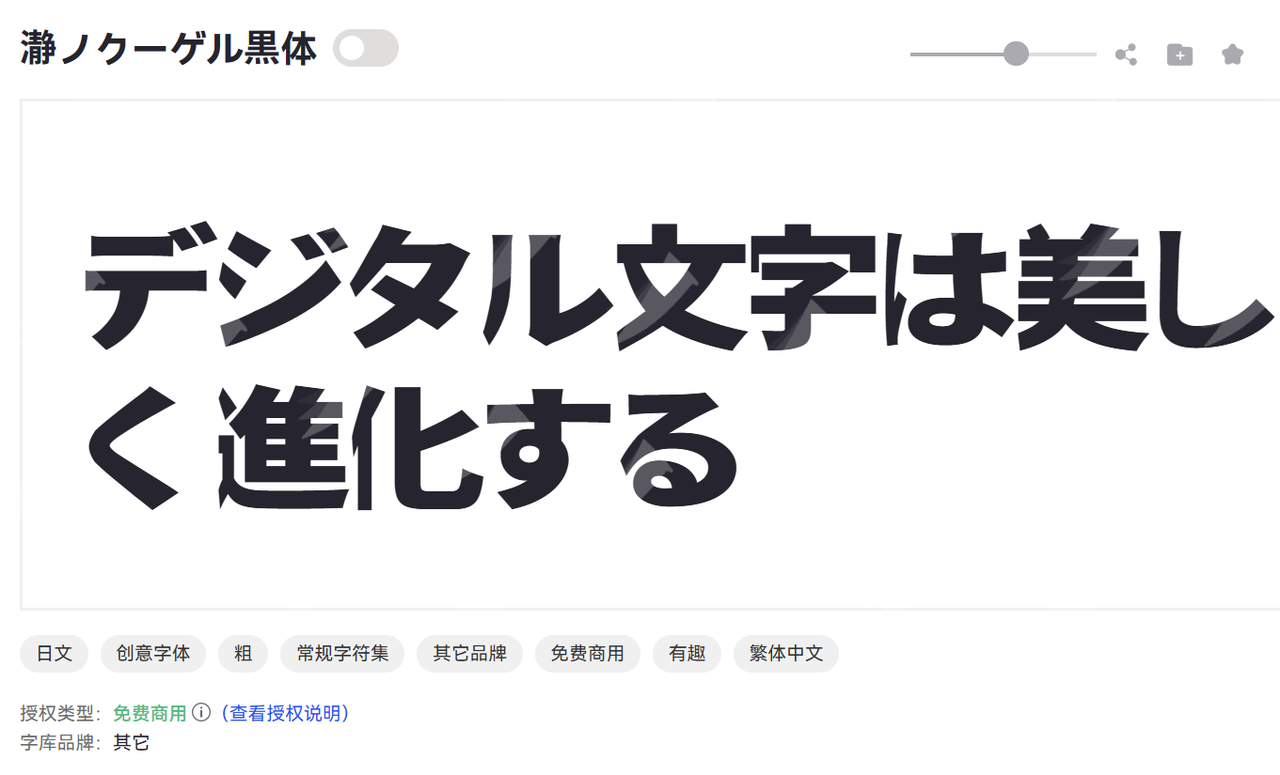
Dela Gothic One Regular
Dela Gothic One Regular是一款极具视觉冲击力的粗体无衬线字体。其笔画粗壮有力,字形结构扎实,强调了力量感和存在感,适合在需要强烈视觉表现的场景中作为标题或醒目文字使用。
字体极其粗壮的笔画使其在任何尺寸下都具备强大的视觉存在感,瞬间吸引眼球。无衬线设计保证了其现代感和简洁性,易于搭配。
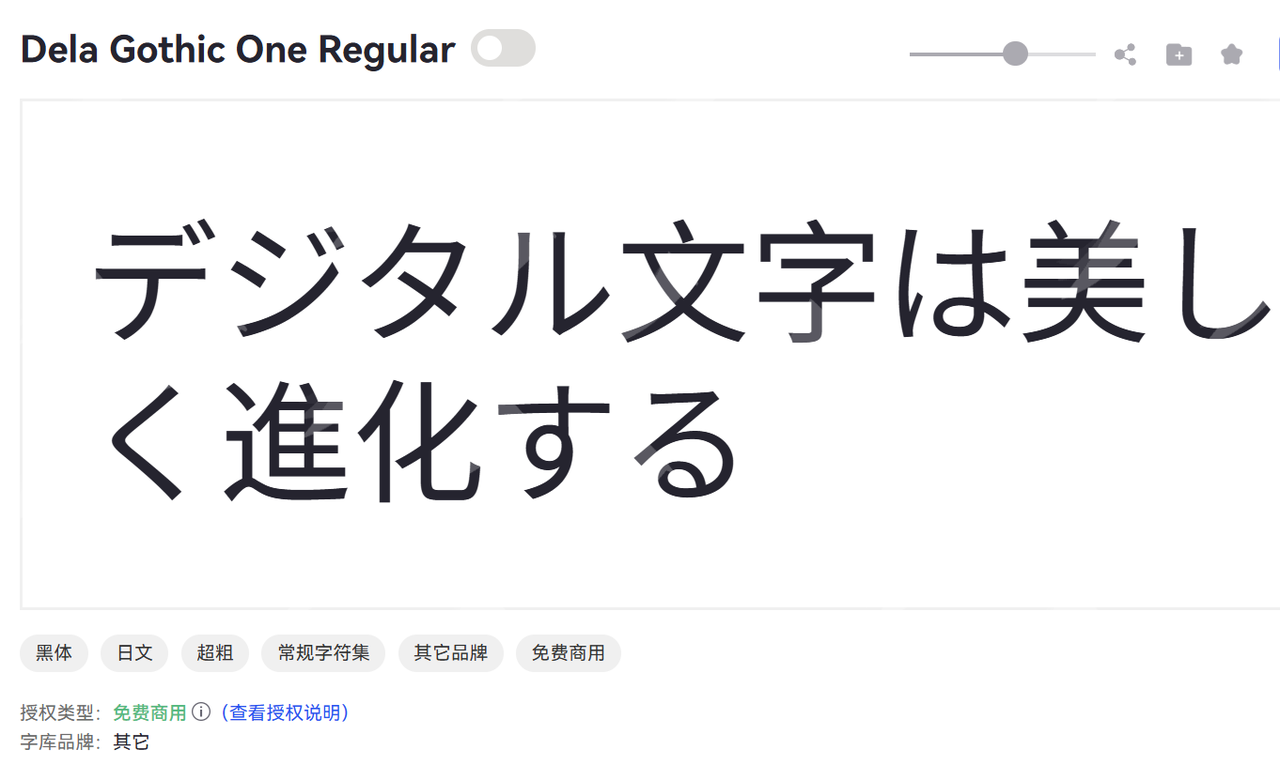
Nishiki-teki
简介:Nishiki-teki笔触流畅而富有变化,结构灵动且不失雅致,笔画的粗细、转折和留白都充满艺术感,赋予文字生命力。适合日式料理店招牌、和服设计、茶道文化宣传、旅游宣传资料等场景。
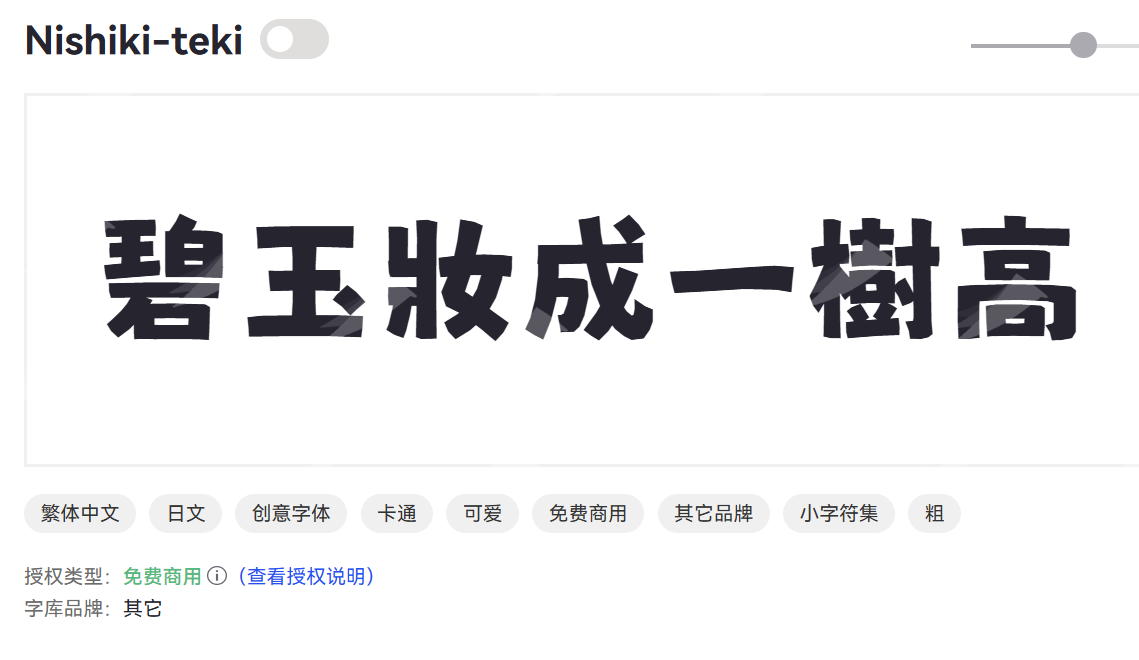
同文新字典体
同文新字典体是一款旨在继承传统字典字体严谨规范的同时,融入现代审美和易读性优化的字体。保持字形端正、笔画清晰的基础上,对细节进行打磨,使其既有历史感又不失现代感。
同文新字典体继承了字典字体的端庄与精确,字形结构严谨。优化了笔画细节,确保在长时间阅读下也能保持舒适度。
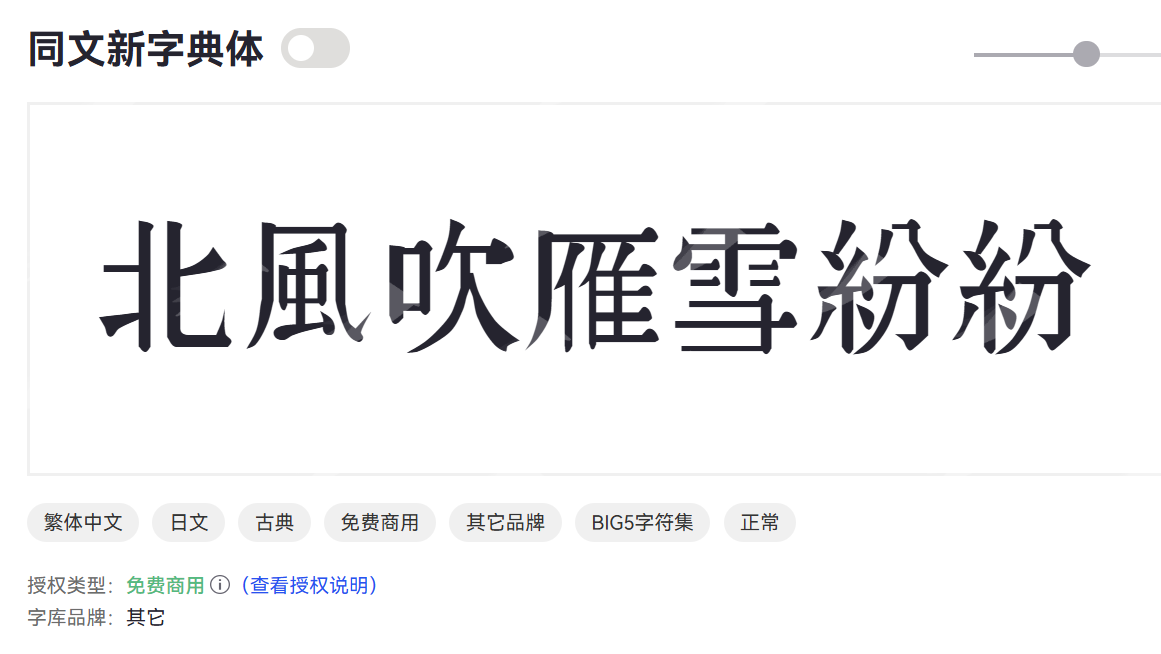
IdeaFonts LongFeiZhengKai JP
IdeaFonts LongFeiZhengKai JP 是一款具有日本书写风格的方正楷体。它在保留了正楷字体的端庄与清晰度的基础上,融入了日式书法的笔触特点,使得字体在严谨中带有几分灵动和独特韵味。
字体继承了正楷字体的工整、规范,适合正式场合。字形结构清晰,即使是小字号也能保持良好的可读性。
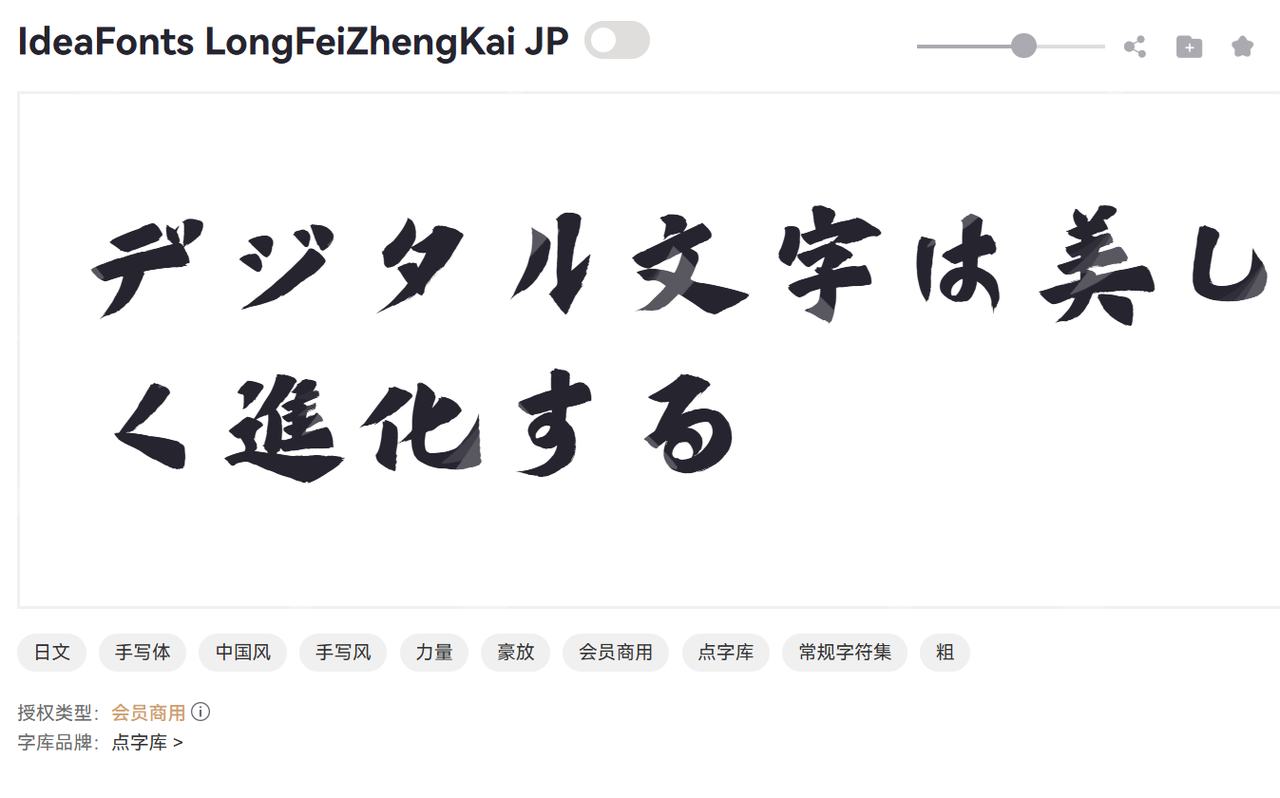
IdeaFonts LongFeiXingShu JP
IdeaFonts LongFeiXingShu JP 是一款充满日式书写风格的行书字体。它在保留行书的连贯流畅和笔墨韵味的同时,融入了日本书法的独特笔触和结构特点。
字体笔画连贯,富有行书特有的动感和节奏感。融合了日本书法的线条美感和结构特点,独具风格。
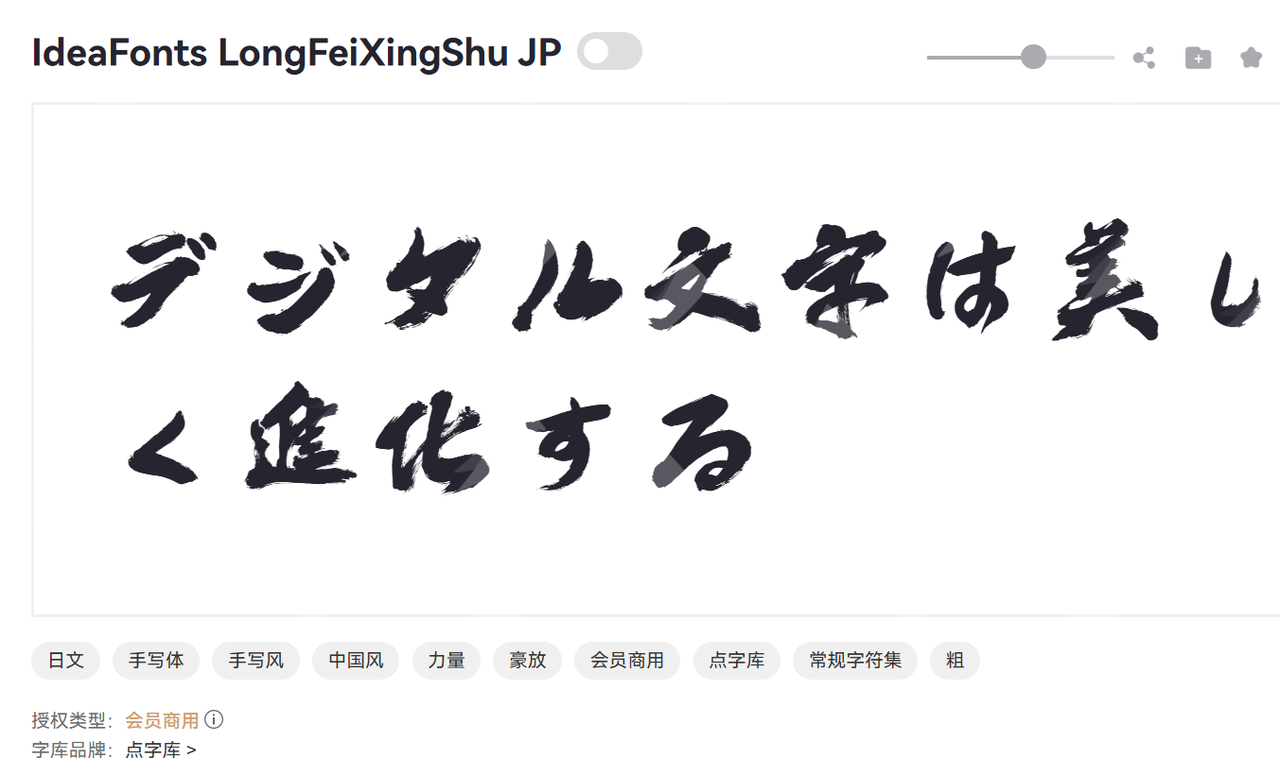
Sankeikaishotai
简Sankeikaishotai 是一款端庄严谨的楷书字体。它秉承了楷书的工整规范和笔画分明,字形结构方正饱满,整体呈现出一种沉稳、清晰且富有古典美的视觉效果。
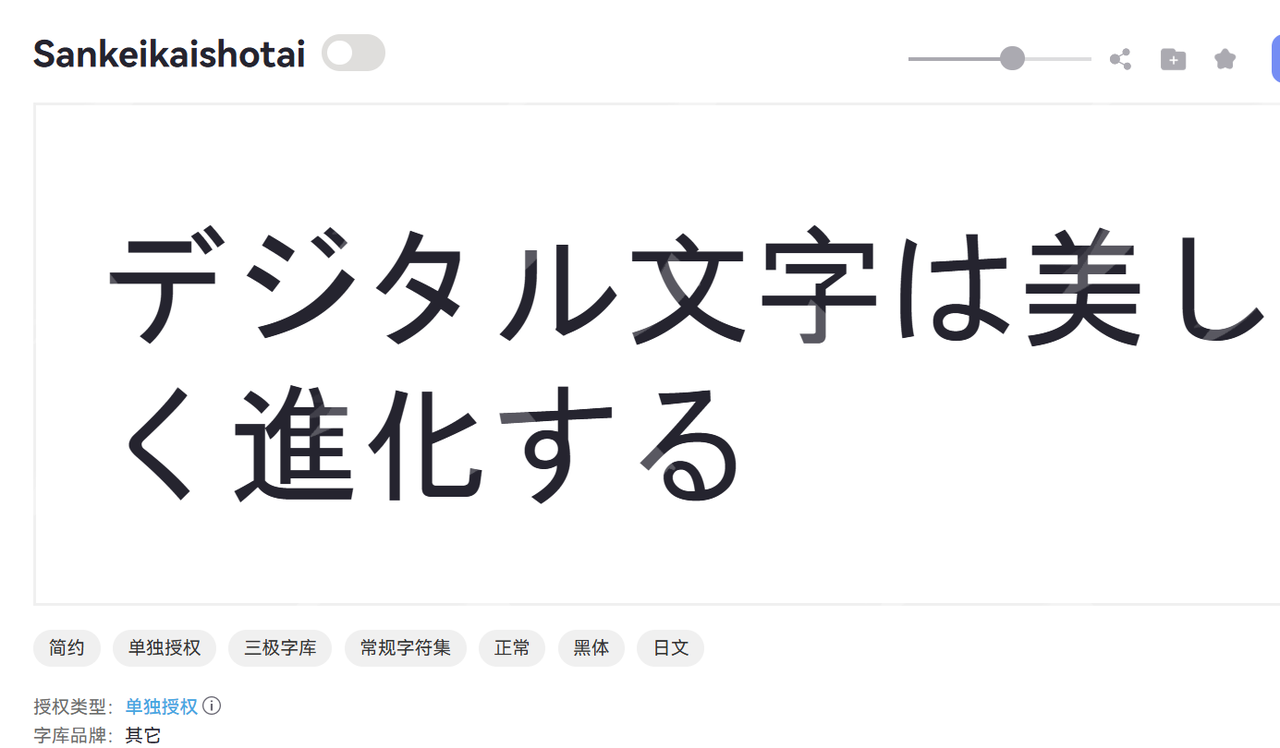
SankeiMaAporo
SankeiMaAporo,可能是一款融合了现代感和独特设计元素的字体,具体风格可能介于无衬线和装饰字体之间,旨在创造一种既简洁又具有视觉吸引力的效果。
Gammill
Gammill通常指的是一种用于绗缝机的品牌,但作为字体,它可能是一款带有工业感、机械感或某种特定几何特征的字体。其设计注重线条的精准和结构的规整,传递出一种专业而实用的美感。
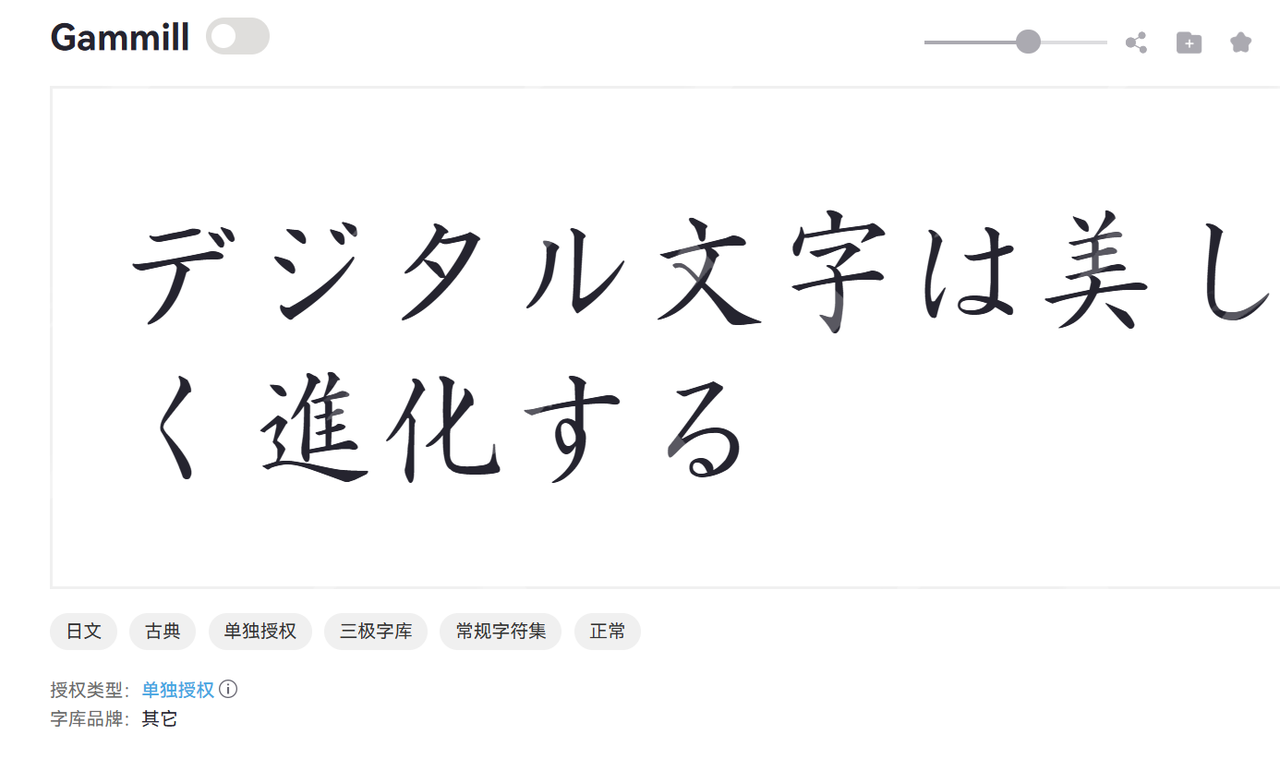
SankeiCutePopanime
SankeiCutePopanime是一款专为动漫、卡通及流行文化设计的字体。它融合了可爱、活泼和动感的元素,笔画通常圆润而富有弹性,字形夸张有趣,充满二次元的魅力。